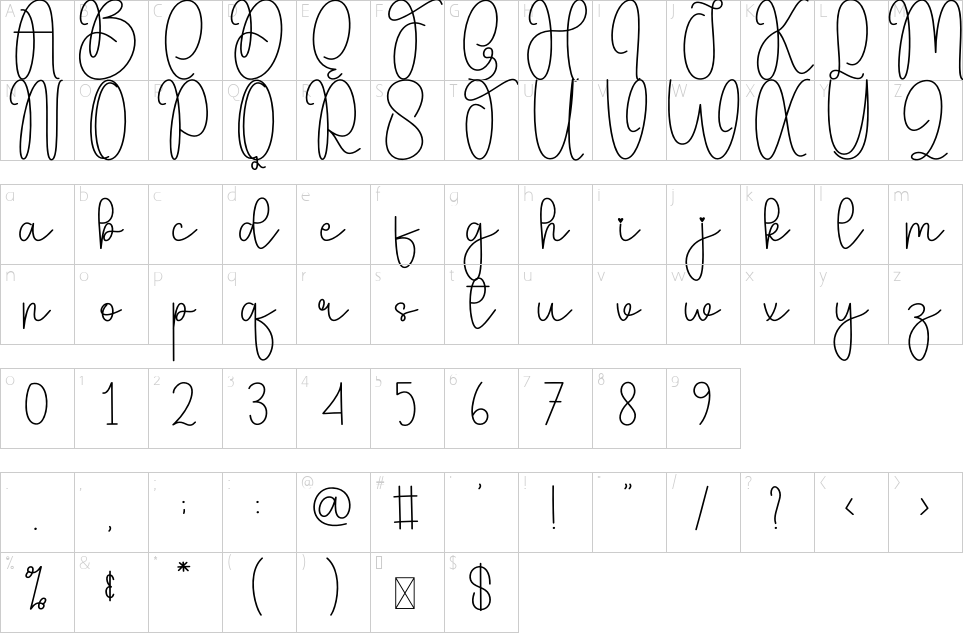
Descobrimos uma fonte surpreendente chamada Santa Birthday, criada por scratchones e disponível de graça. Esta fonte, perfeita para criar cartões de aniversário natalinos ou decorações de festas, tem uma aparência festiva e encantadora. Seja em Windows ou Mac, você pode baixar esta fonte e personalizar suas criações de forma única para celebrar a chegada do Papai Noel. Com um design minimalista e uma aparência colorida, Santa Birthday é a escolha perfeita para criar um toque especial em seu próximo projeto gráfico. Até o próximo projeto, não esqueça de baixar Santa Birthday para tornar suas criações ainda mais amigáveis e natalinos.